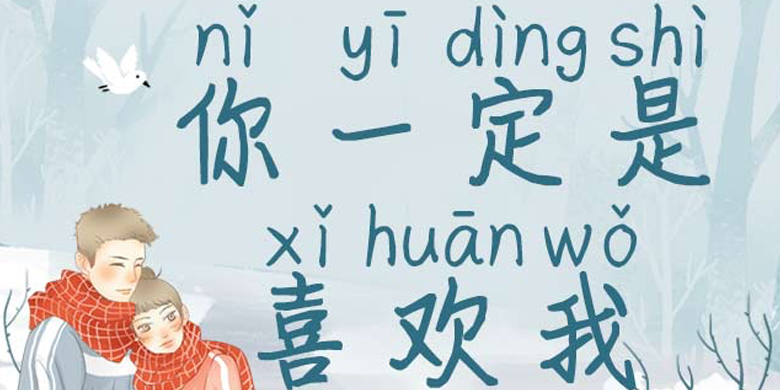
方正手迹-你一定是喜欢我
字体品牌: 方正手迹 设计师:王航 字体分类:创意书写 字体属性:精品字 字符集:大陆简体(GB2312-80) 发布时间: 2020
粗细变化小,一笔一划的起笔收笔,能感受到作者写字时得真诚,阅读起来丝毫不费劲。适用于少年儿童类的书刊、品牌广告和产品包装设计,以及社交网络的个性化用字。